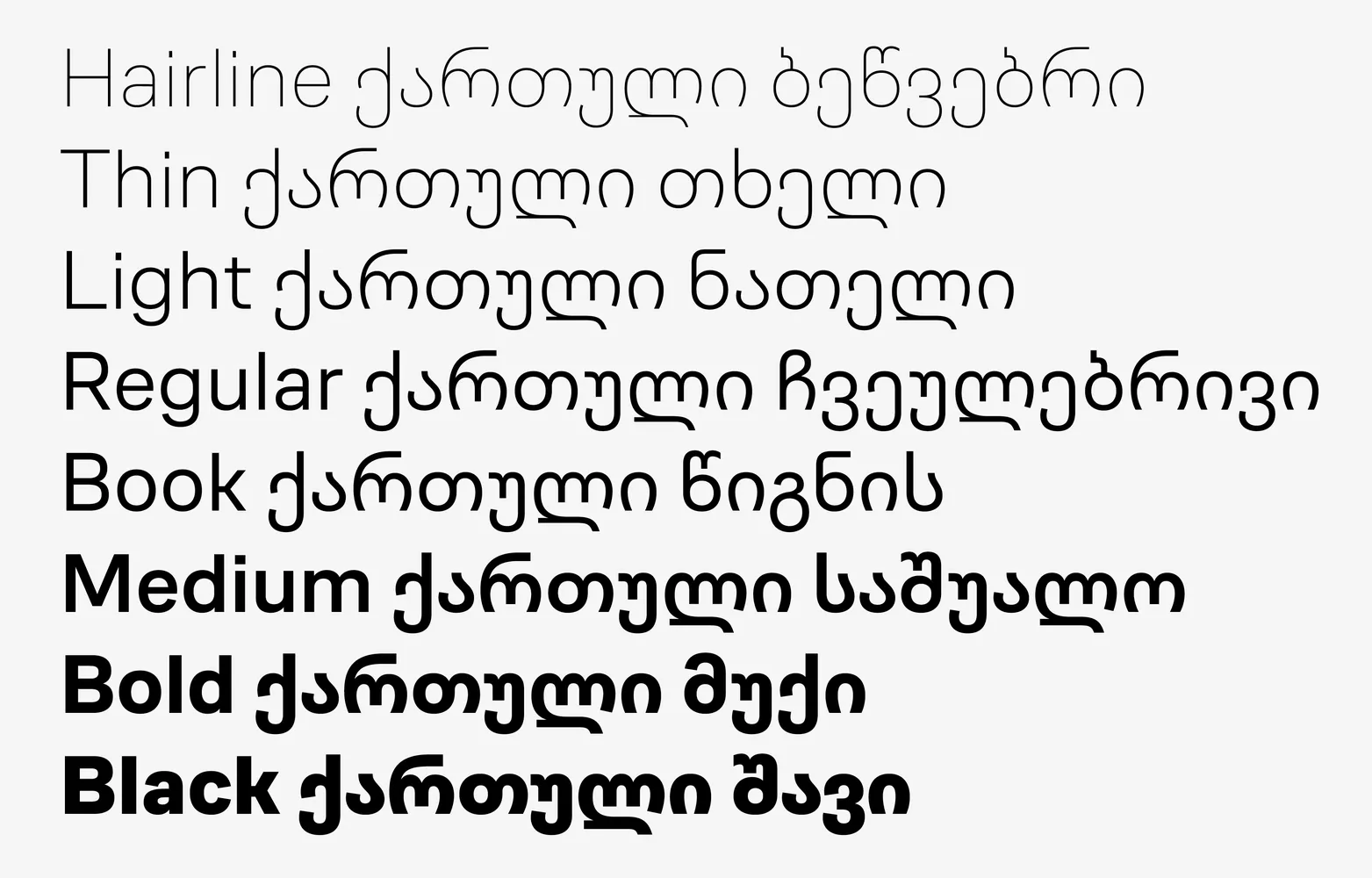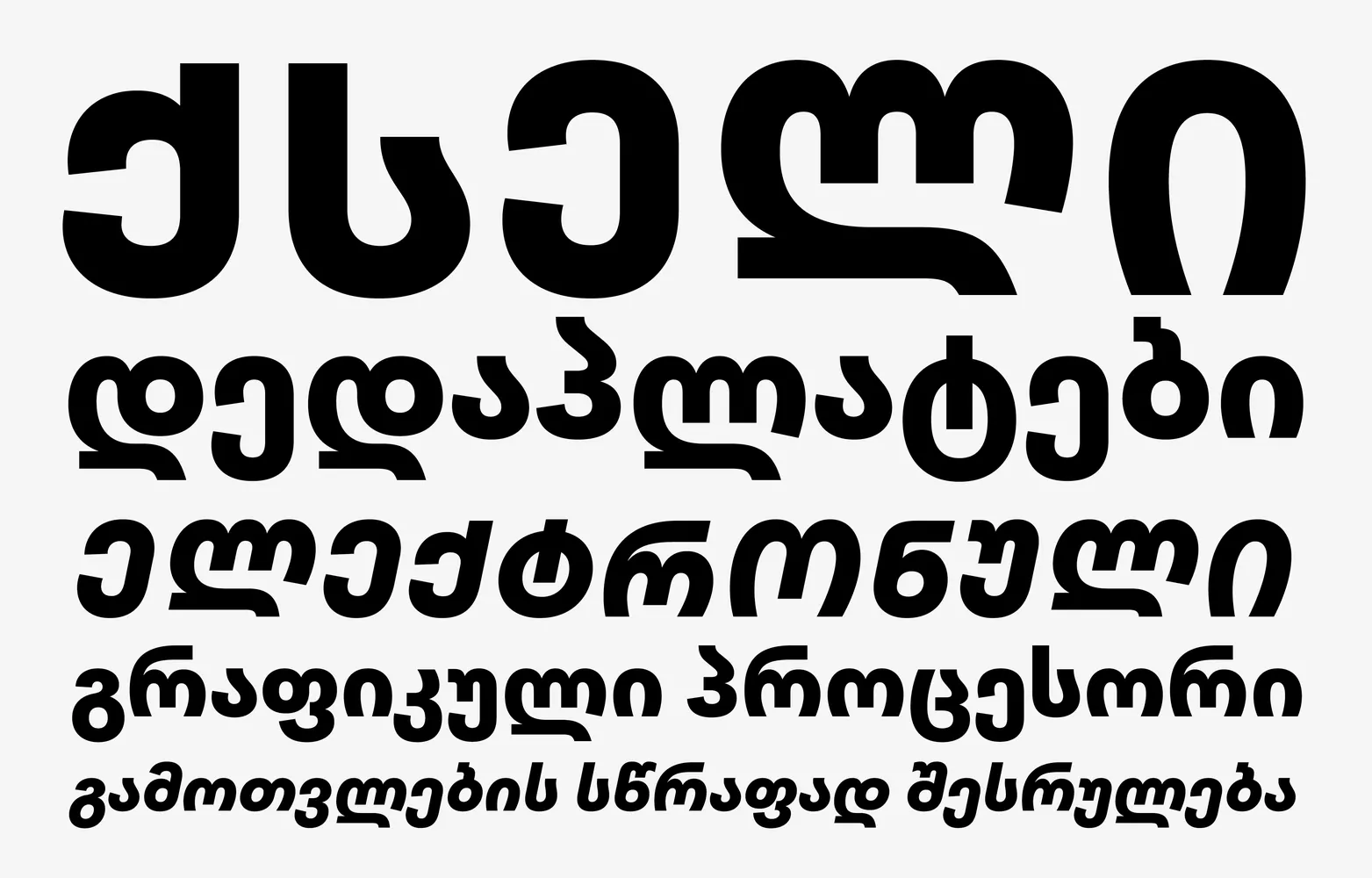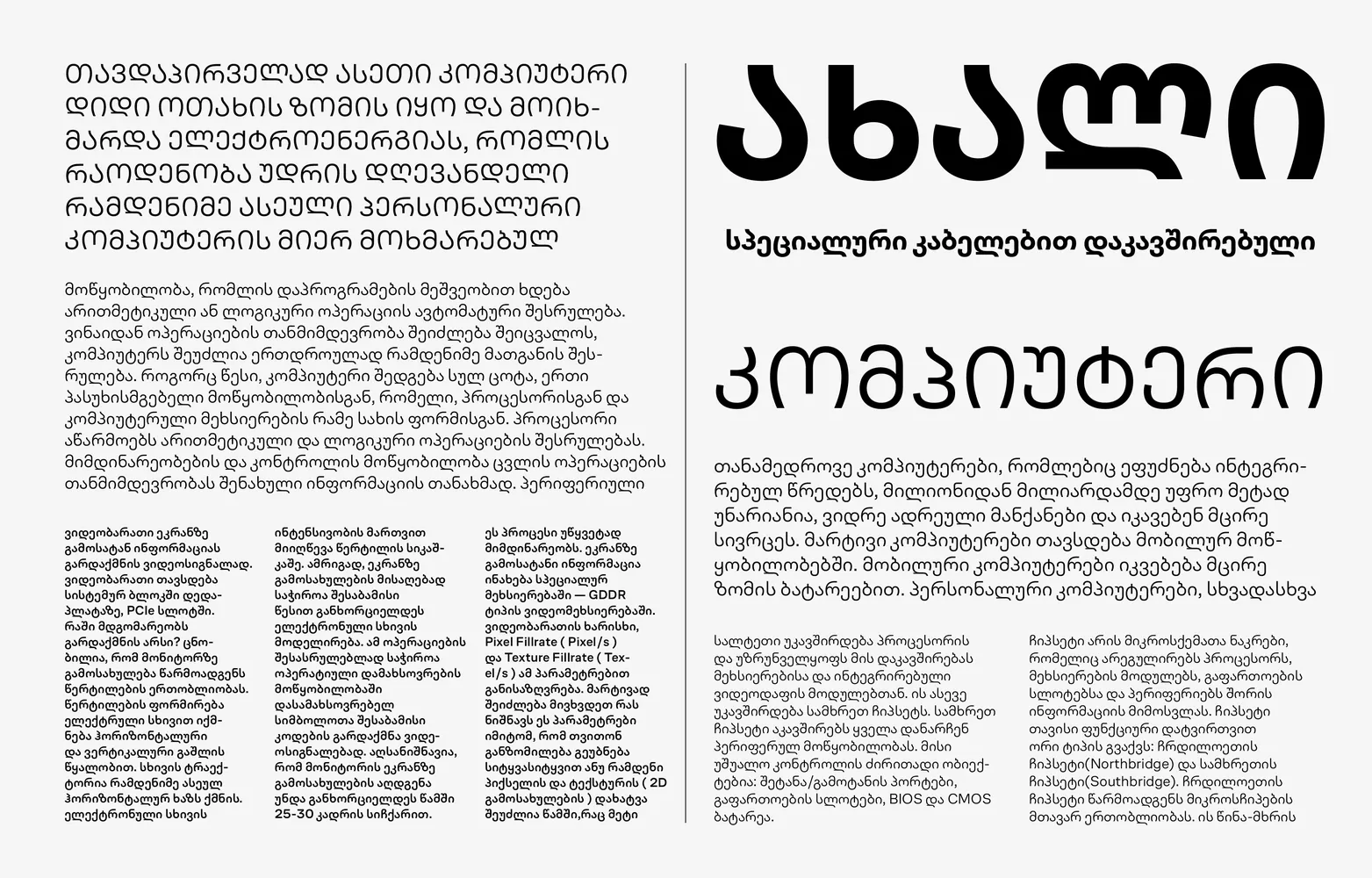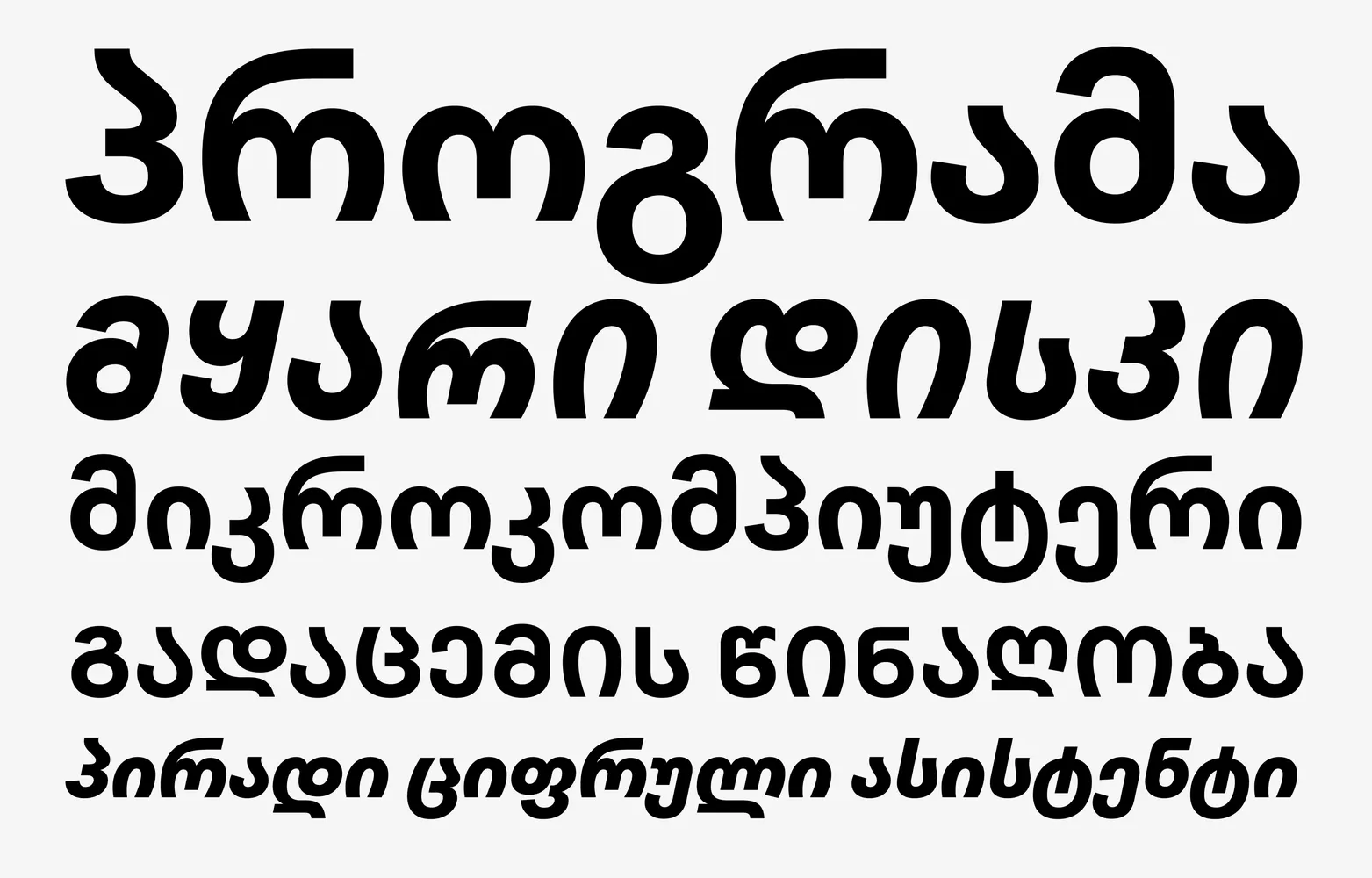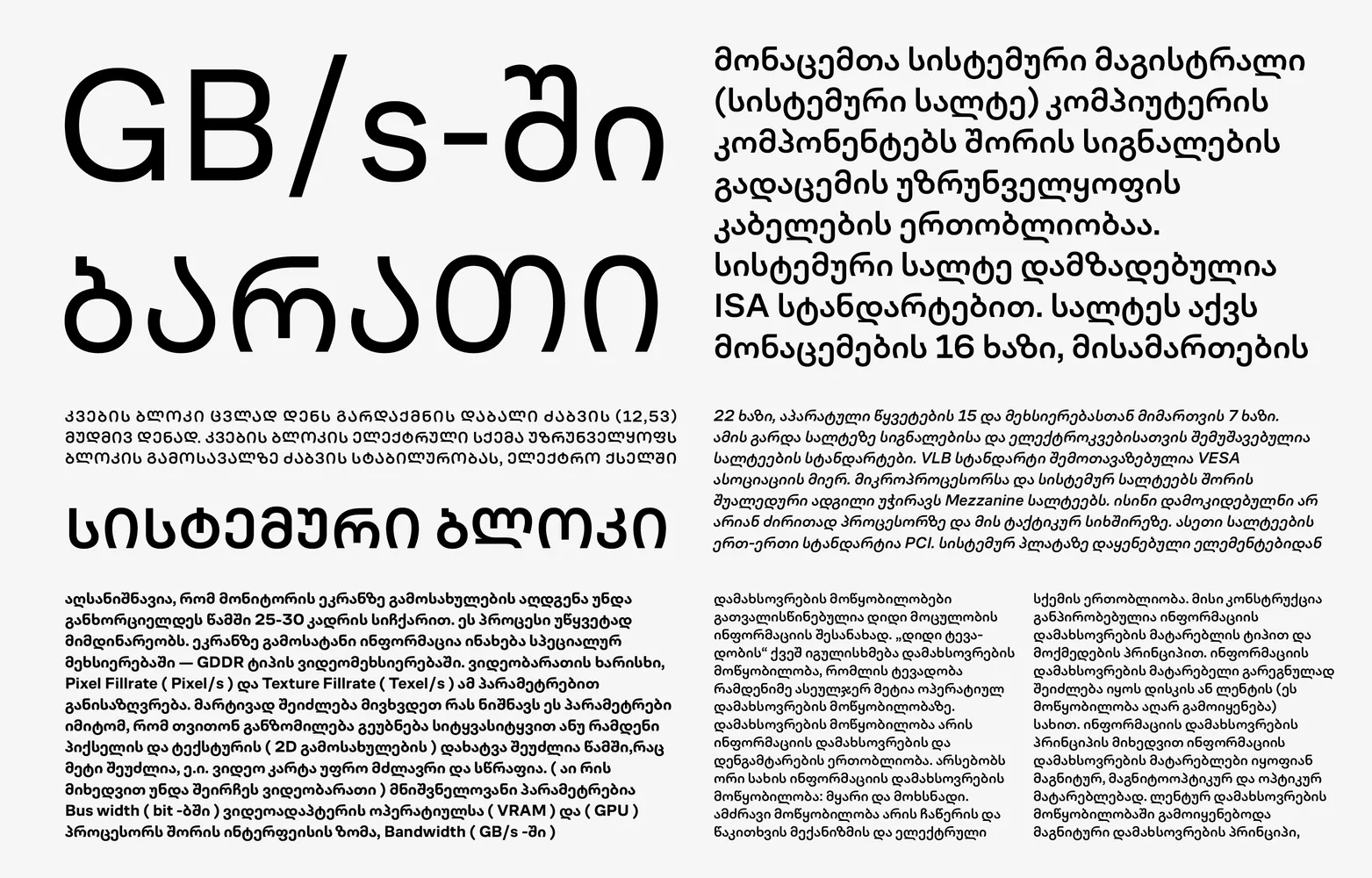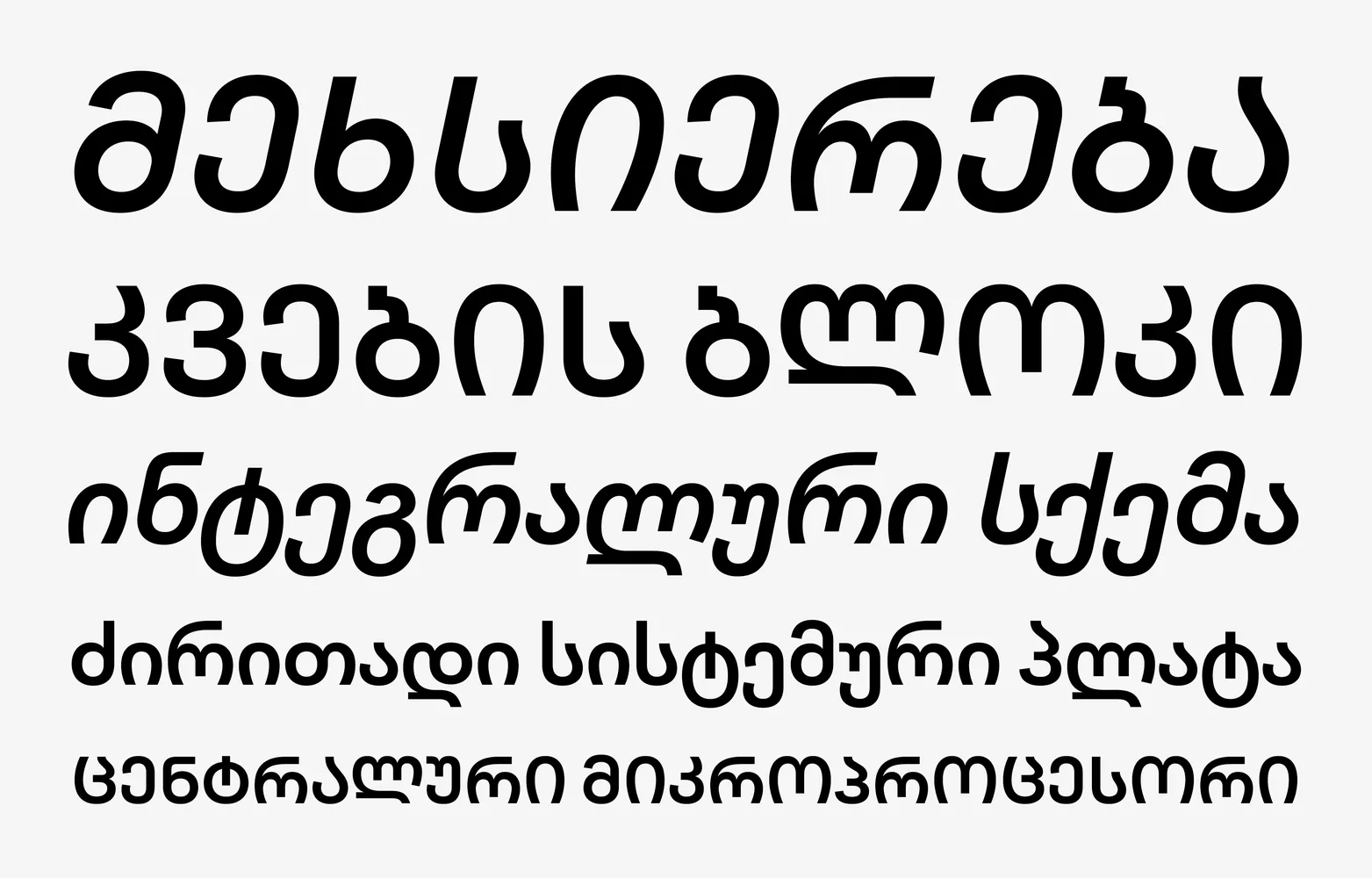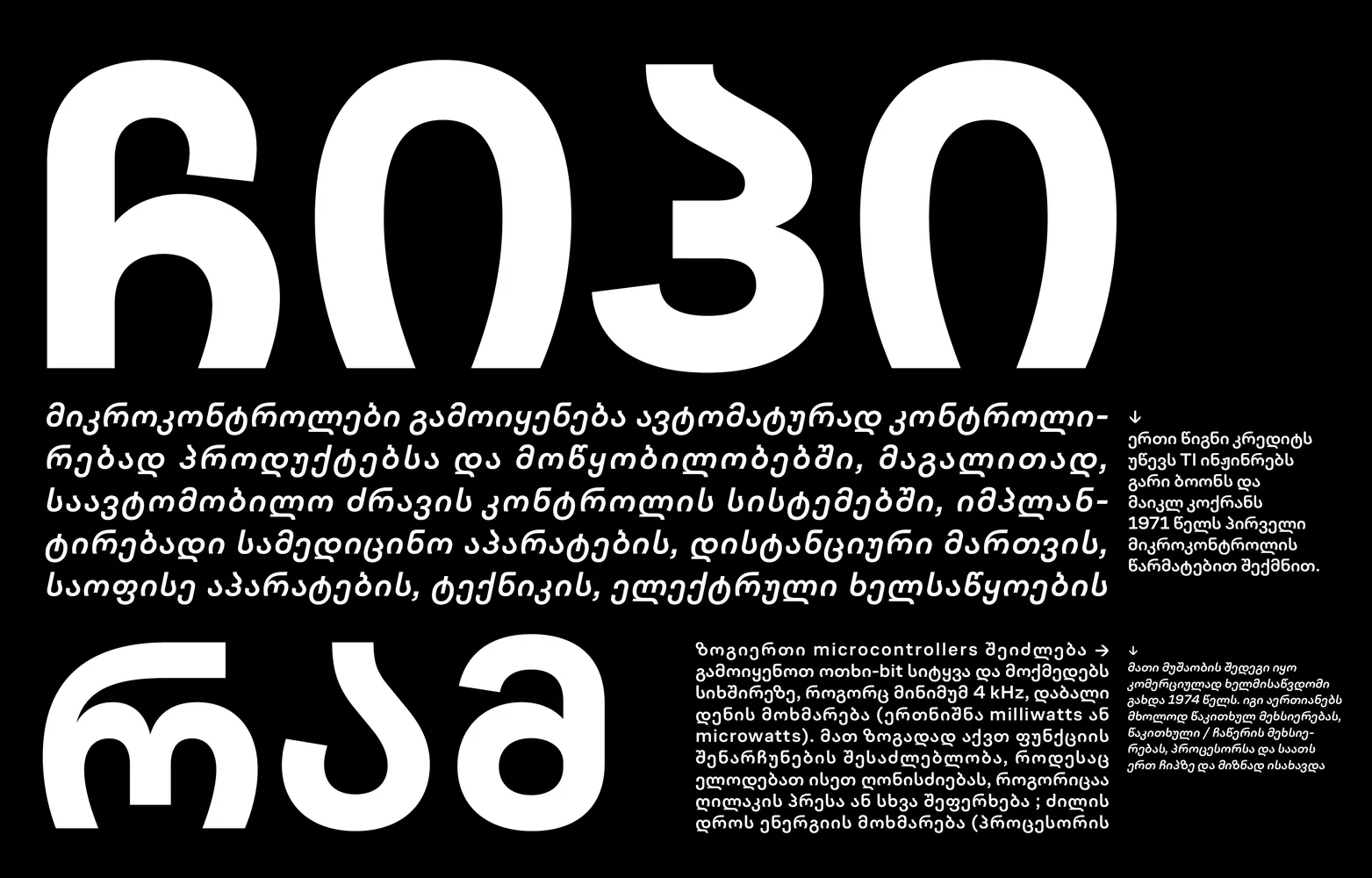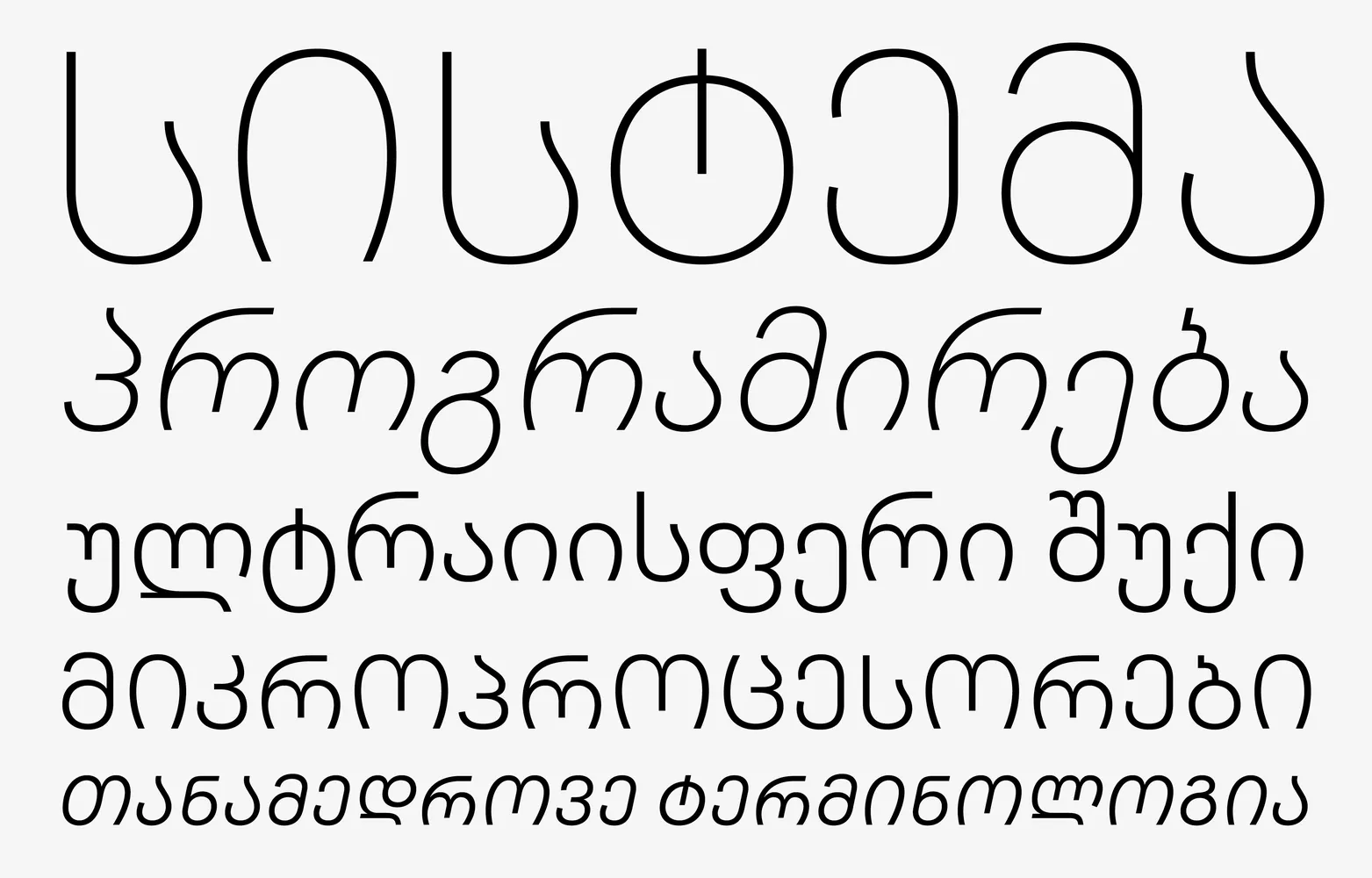
CoFo Sans Georgian—продолжение чистой и рациональной эстетики CoFo Sans, адаптированное для грузинской письменности. Шрифт сохраняет равновесие между строгой конструкцией и выразительными деталями. Он понятный и удобный, с мягкой интонацией, но не безликий.
Грузинская письменность органично встраивается в стиль семейства. Удлинённые выносные элементы и оптимальная высота строчных знаков задают ровный ритм набора, сохраняя при этом естественную читаемость грузинских букв и плотность текста. Широкие внутрибуквенные просветы, лёгкая квадратность форм и сдержанная пластика придают набору современный, уверенный вид. А большой выбор начертаний и компактные вертикальные пропорции делают CoFo Sans Georgian подходящим грузинским шрифтом для сложных типографских задач.
Созданный для экранов, CoFo Sans Georgian решает главную задачу грузинской типографики: обеспечивает читаемость даже при плотном интерлиньяже. Шрифт стабильно работает в интерфейсах, приложениях и длинных текстах. Грузинская версия дополняет систему CoFo Sans как элемент единого современного шрифтового семейства, созданного для чёткой и гибкой коммуникации между разными алфавитами.
Начертания: Hairline, Hairline Italic, Thin, Thin Italic, Light, Light Italic, Regular, Regular Italic, Book, Book Italic, Medium, Medium Italic, Bold, Bold Italic, Black, Black Italic